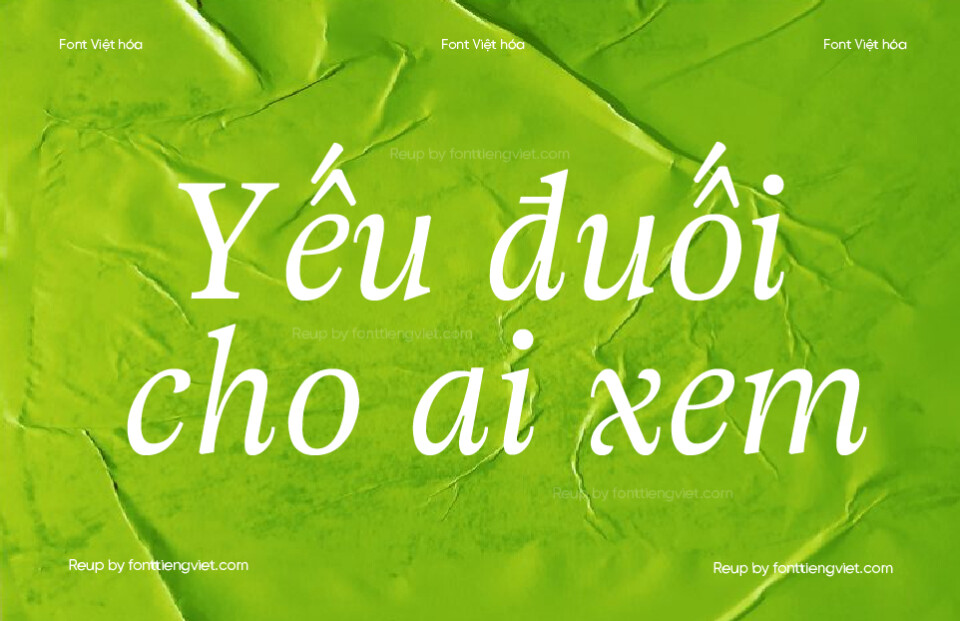
Trong thế giới thiết kế đồ họa và typography, việc lựa chọn một Font Chữ đẹp và phù hợp có thể quyết định đến 50% sự thành công của một dự án. Hôm nay, chúng ta sẽ đi sâu vào một tuyệt phẩm đã được cộng đồng thiết kế Việt Nam đón nhận nồng nhiệt: Font Việt hóa UTM Adriane Swash. Đây không chỉ là một bộ font thông thường; nó là sự kết hợp hoàn hảo giữa nét cổ điển sang trọng và hơi thở hiện đại, mang lại sự tinh tế và cá tính cho mọi ấn phẩm. Nếu bạn đang tìm kiếm một giải pháp typography chất lượng cao, đã được tối ưu cho tiếng Việt, đặc biệt là cho các thiết kế thiệp cưới, logo cao cấp, hay các dự án mang tính nghệ thuật, UTM Adriane Swash chính là lựa chọn không thể bỏ qua. Bài viết này sẽ cung cấp cái nhìn chi tiết nhất về đặc điểm, cách sử dụng, và lý do vì sao bộ font này lại trở nên phổ biến đến vậy.
Giới Thiệu Tổng Quan về Font Việt hóa UTM Adriane Swash
Adriane Swash ban đầu là một font chữ quốc tế nổi tiếng với phong cách script (chữ viết tay) hoặc serif kết hợp swash (nét uốn lượn). Khi được nhóm UTM (Upright Type Measurement) tiến hành Việt hóa, bộ font này không chỉ giữ nguyên được vẻ đẹp và sự thanh thoát vốn có mà còn được bổ sung đầy đủ các ký tự tiếng Việt, dấu thanh, và kerning (khoảng cách giữa các chữ) được căn chỉnh tỉ mỉ. Việc Việt hóa này là cực kỳ quan trọng, đảm bảo rằng khi bạn sử dụng Font Việt hóa UTM Adriane Swash để viết các đoạn văn bản tiếng Việt, các dấu và ký tự đặc biệt không bị lỗi, mang lại tính thẩm mỹ đồng nhất xuyên suốt tác phẩm. Sự chú trọng vào chi tiết này đã biến nó thành công cụ đắc lực cho các nhà thiết kế ở Việt Nam, giúp họ tạo ra những sản phẩm chuyên nghiệp mà không cần lo lắng về vấn đề hiển thị font.
Nguồn Gốc và Phong Cách Thiết Kế
Phong cách của UTM Adriane Swash nằm ở sự kết hợp giữa chữ viết tay bay bổng và sự vững chãi của các nét chữ có độ dày mỏng khác nhau (high contrast). Điểm nhấn chính là các ‘swashes’ – những đường cong, đường lượn tinh tế kéo dài ra khỏi chữ cái, thường thấy ở các chữ cái đầu hoặc cuối câu. Sự xuất hiện của các swashes này làm tăng tính nghệ thuật, kịch tính và sự lãng mạn cho văn bản, khiến nó trở nên lý tưởng cho các ấn phẩm cần sự sang trọng, chẳng hạn như bìa sách, nhãn hiệu mỹ phẩm cao cấp, hoặc backdrop chụp ảnh. Độ tương phản rõ rệt giữa nét dày và nét mảnh mô phỏng phong cách calligraphy (thư pháp) cổ điển, nhưng với sự sắc nét của thiết kế digital hiện đại.
Đặc Điểm Nổi Bật và Lý Do Font UTM Adriane Swash Được Yêu Thích
Không giống như các font chữ sans-serif đơn giản, UTM Adriane Swash đòi hỏi sự tinh tế trong cách sử dụng. Sự yêu thích mà cộng đồng thiết kế dành cho bộ font này đến từ khả năng biến hóa tuyệt vời của nó, từ một tiêu đề mạnh mẽ đến một lời mời trang trọng.
Sự Thanh Lịch Trong Từng Nét Chữ
Các glyph (hình dạng chữ cái) trong bộ font này được thiết kế với sự chăm chút đặc biệt. Mỗi chữ cái được tối ưu hóa để tương tác hài hòa với các chữ cái lân cận. Đối với các dự án liên quan đến trường học, học sinh, hoặc các buổi lễ tốt nghiệp quan trọng, việc sử dụng font này cho tiêu đề hoặc lời đề tặng sẽ làm tăng sự trang trọng, nhấn mạnh tính kỷ niệm và giá trị của sự kiện. Khi các học sinh cấp 3 chuẩn bị cho các kỳ thi tốt nghiệp quan trọng, một thiết kế tài liệu học tập với font chữ đẹp mắt cũng có thể tạo cảm hứng học tập tốt hơn.
Tính Ứng Dụng Cao Trong Thiết Kế Thương Mại
Mặc dù mang tính nghệ thuật cao, UTM Adriane Swash lại có tính ứng dụng rất rộng. Nó được sử dụng phổ biến nhất trong:
- Thiết Kế Logo: Đặc biệt cho các thương hiệu thời trang, trang sức, hoặc dịch vụ cưới hỏi.
- Thiệp Mời: Từ thiệp sinh nhật đến thiệp cưới, font mang lại sự độc đáo và cá nhân hóa.
- Bao Bì Sản Phẩm: Giúp các sản phẩm cao cấp truyền tải thông điệp về chất lượng và sự tinh xảo.
- Ấn Phẩm Giáo Dục Đặc Biệt: Dùng làm tiêu đề cho các bằng khen, chứng chỉ, và các tài liệu liên quan đến buổi lễ tốt nghiệp cấp 3.
Lưu Ý Khi Sử Dụng Font UTM Adriane Swash Trong Các Dự Án Lớn
Khi làm việc với các font chữ mang phong cách swash mạnh mẽ như UTM Adriane Swash, điều quan trọng là phải biết cách phối hợp font. Do tính chất nổi bật và chi tiết của nó, UTM Adriane Swash nên được sử dụng chủ yếu cho tiêu đề (headings) hoặc các đoạn văn bản ngắn cần sự nhấn mạnh. Tránh sử dụng nó cho các đoạn văn bản dài vì nó có thể gây khó đọc và rối mắt. Hãy kết hợp nó với một font chữ sans-serif hoặc serif đơn giản, sạch sẽ (ví dụ: Montserrat, Roboto, hoặc Times New Roman) cho nội dung thân bài để tạo ra sự cân bằng hoàn hảo trong bố cục typography. Việc áp dụng đúng nguyên tắc này sẽ giúp thiết kế của bạn vừa ấn tượng, vừa đảm bảo tính dễ đọc, điều mà các nhà thiết kế chuyên nghiệp luôn hướng tới khi tạo ra các tài liệu quan trọng cho sinh viên hay các ấn phẩm giáo dục khác.
Sự ra đời và phổ biến của Font Việt hóa UTM Adriane Swash đã chứng minh tầm quan trọng của việc Việt hóa các tài nguyên thiết kế chất lượng cao. Nó không chỉ là công cụ mà còn là nguồn cảm hứng cho vô số dự án sáng tạo, từ những tấm thiệp mời cá nhân cho đến các chiến dịch thương hiệu quy mô lớn. Với khả năng tương thích cao và vẻ ngoài không thể nhầm lẫn, đây chắc chắn là một tài sản quý giá trong thư viện font của bất kỳ nhà thiết kế nào. Nếu bạn đang tìm kiếm những bộ Font Chữ độc đáo và đã được tối ưu hóa tiếng Việt khác, hãy tiếp tục khám phá. Chúc bạn thành công với những thiết kế đầy sáng tạo của mình!